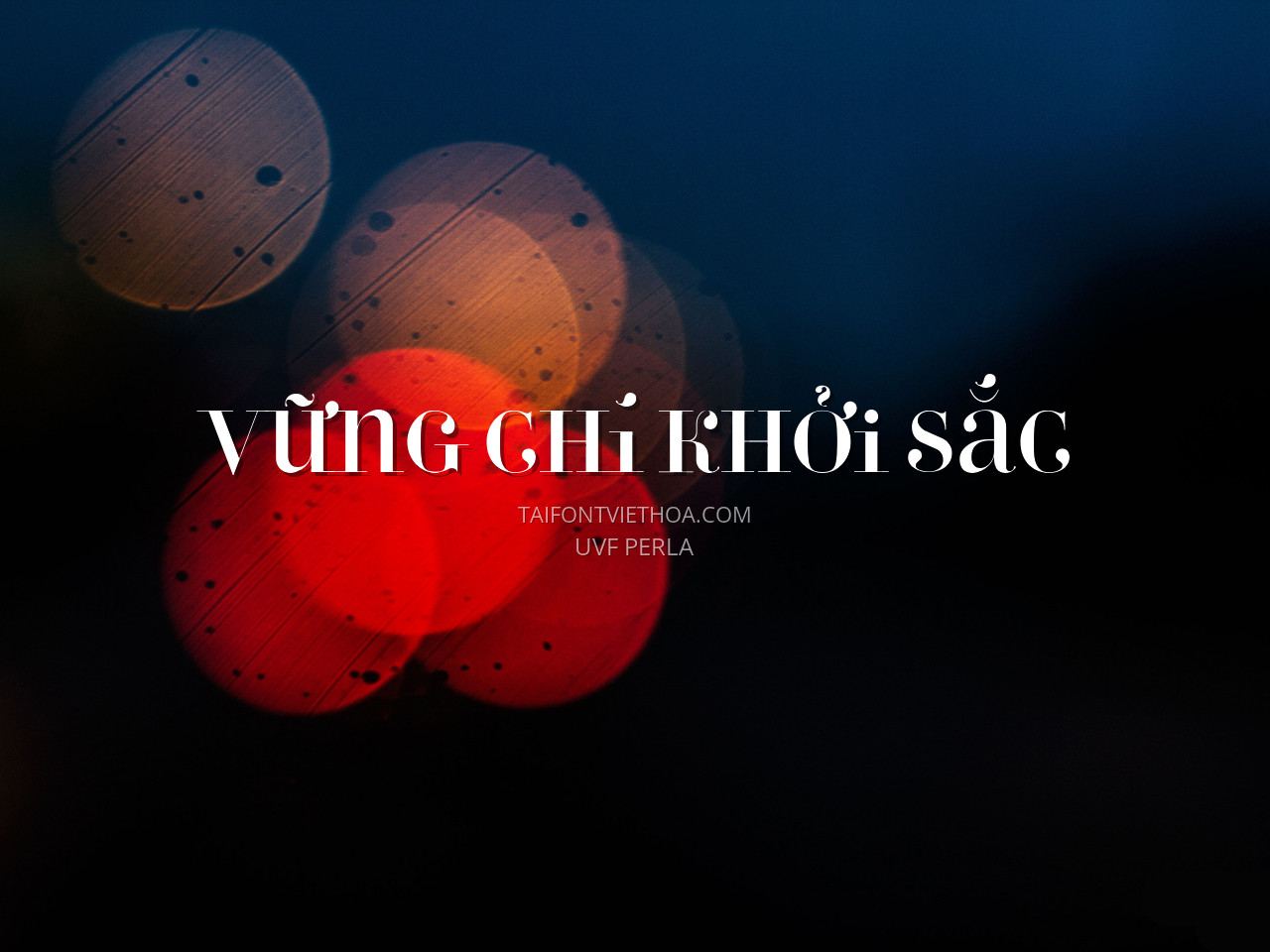
Font việt hóa UVF Perla
Giới thiệu về font UVF Perla
UVF Perla là một kiểu chữ serif hiện đại mang phong cách thời thượng và sang trọng, với điểm nhấn nằm ở các đường cong thanh mảnh và hình khối sắc nét. Font được thiết kế với tinh thần tối giản nhưng đầy tính thẩm mỹ, thường xuất hiện trên các nền tảng font quốc tế như MyFonts, Behance và FontsArena. Bên cạnh việc hỗ trợ tiếng Việt, font còn tương thích với hơn 200 ngôn ngữ khác, đáp ứng nhu cầu thiết kế toàn cầu.
Phiên bản Việt hóa mang tên UVF Perla đã được thành viên Font Chuẩn sưu tầm và chia sẻ, được taifontviethoa.com chọn lọc nhằm phục vụ cộng đồng thiết kế Việt Nam trong các ứng dụng thực tế như bộ nhận diện thương hiệu, ấn phẩm quảng cáo, in ấn sáng tạo và truyền thông sự kiện. Với khả năng trình bày tiếng Việt chính xác, font này không chỉ giúp tiết kiệm thời gian xử lý văn bản mà còn tăng giá trị thẩm mỹ cho tổng thể thiết kế.
Đặc điểm thiết kế và ứng dụng của UVF Perla
UVF Perla sở hữu các đường nét gọn gàng, tỷ lệ hài hòa giữa phần thân chính và phần chân chữ (serif) mảnh mai nhưng chắc chắn. Độ tương phản giữa các nét chính – phụ được cân chỉnh tinh tế, tạo cảm giác nhẹ nhàng nhưng không thiếu điểm nhấn thị giác. Font không chỉ có các ký tự cơ bản mà còn đi kèm nhiều ligature và dạng thay thế stylistic, giúp tăng tính cá nhân hóa cho thiết kế.
UVF Perla rất phù hợp với các ứng dụng như: thiết kế logo cao cấp, bao bì mỹ phẩm, poster nghệ thuật, bìa sách, namecard hoặc các trang in ấn thương hiệu. Với chất lượng thẩm mỹ vượt trội, font được đánh giá là phù hợp với các ngành nghề như: thời trang, làm đẹp, sự kiện, nội thất cao cấp, xuất bản và quảng cáo.